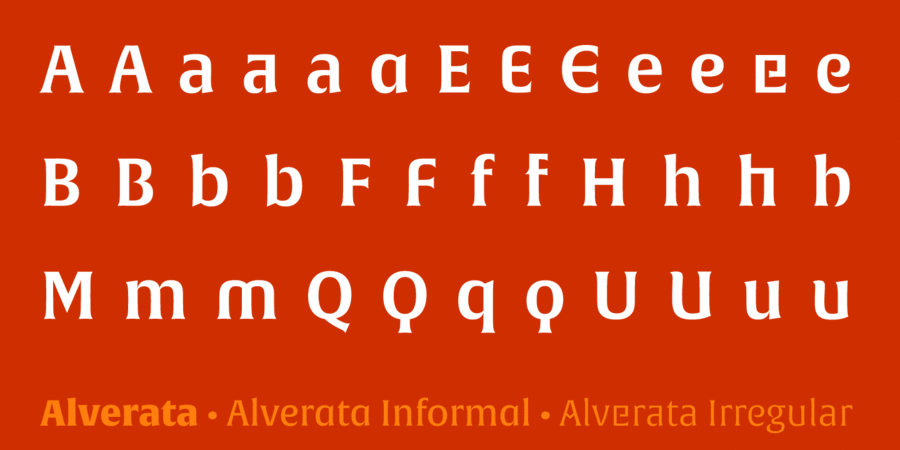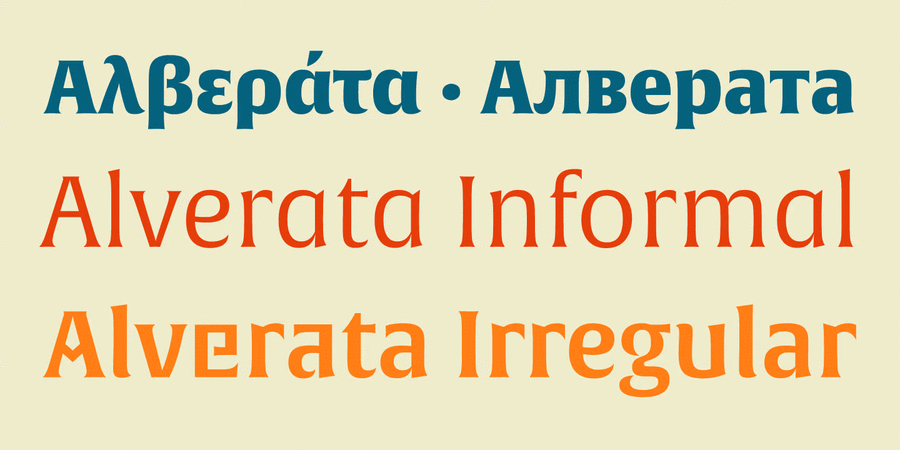
Alverata Cyrillic – це сучасна електична шрифтова родина, натхненна шрифтовими формами середньовічної Європи. Основою цього шрифту є капітальний лист, вплив якого можна побачити в його коротких засічках шиповидних і розкльошених штрихах. Alverata також експериментує з самими графемами, змінюючи прямі лінії на криві та навпаки. Гарнітура чудово справляється як із цифровим, так і з фізичним застосуванням, забезпечуючи відмінну відкритість та розбірливість дрібного тексту, а також жвавість та привабливість при великих розмірах. Нагороди та відзнаки: ISTD 2014, Typeface Design 2014, Communication Arts, Рутенія 2014, Fontshop’s Best of 2014, Typographica’s Notable Releases of 2014, 2015 European Design Gold Award, Honourable mention in Print Magazine, 2015 Yearbook of Type II, TDC Tokio: Type Design Prize 2016, 50 best typefaces in étapes magazine 2014. Гарнітуру розробив Герард Унґер у 2014 році.
Хіт 1960-х Alverata CYR підтримує 83 мовиУкраїнська, Англійська, Німецька, Польська, Португальська, Іспанська, Французька, Російська, Чеська, Голландська, Італійська, Шведська, Турецька, Фінська, Білоруська, Сербська, Болгарська, Естонська, Литовська, Албанська, Африкаанс, Баскська, Бретонська, Валенсаска, Galician, Гельська (Шотландська), Данська, Індонезійська, Ірландська, Ісландська (Win), Каракалпацька, Каталонська, Норвезька, Окситанська, Ретороманська, Самі Лулі, Тсванська, Узбецька (Лат.), Фарерська, фризька, Чаморро, Естонська (Win), Південносаамська, Албанська (Win), Угорська, Верхньолужицька, Карельська, Латвійська (Mac), Литовська (Mac), Маорійські (Mac), Молдавська (Лат.), Нижньолужицька, Румунська (Win), Словацька, Словенська, Туркменська (Лат.), Хорватська (Win), Естонська (Mac), Курдська, Латишська, Маорійські, Руминська, Абазинська, Аварська, Агульська, Адигейська, Даргинську, Інгуську, Кабардино-Черкеська, Кабардинська, Карачаєво-Балкарська, Кумицька, Лакська, Лезгинська, Македонську, Мордовсько-Мокшанська, Мордовсько-Ерзянська, Ногайська, Рутульська, Табасаранська, Татська, Цахурська, Чеченська Функції сімейства шрифтів Alverata CYRЗастосування гарнітури у верстці:
витончений, ефектний, якісний, культурний, добірний, благородний, гармонійний, елітний, дорогий, розкішний, красивий, елегантний, ювелірний, майстерний, естетичний, художній, знаменитий, дорогоцінний, оригінальний, багатий, міський, гострий, виразний, характерний, прекрасний, динамічний, аристократичний, історичний, традиційний, унікальний, ностальгічний, світський, цікавий, гуманітарний, фантастичний, пафосний, старовинний, імперський, сакральний, релігійний, біблійний, церковний, срібний, ввічливий, королівський, сексуальний, яскравий, артистичний, кам'яний, легендарний, різкий, гордий, переконливий, твердий, стійкий, авторитетний, дзвінкий, героїчний, лицарський, сміливий, старомодний, казковий, пивний, золотий, святковий, сильний, мотивуючий, помітний, фундаментальний, урочистий, епічний, амбітний, римський, владний, видовищний, грандіозний, великий, величний, монументальний, впевнений, архітектурний, кінематографічний, християнський, смачний, апетитний, колючий, дивний, чіткий, серйозний, жорсткий, залізний, сталевий, незвичайний, карбований, важливий, експериментальний, активний